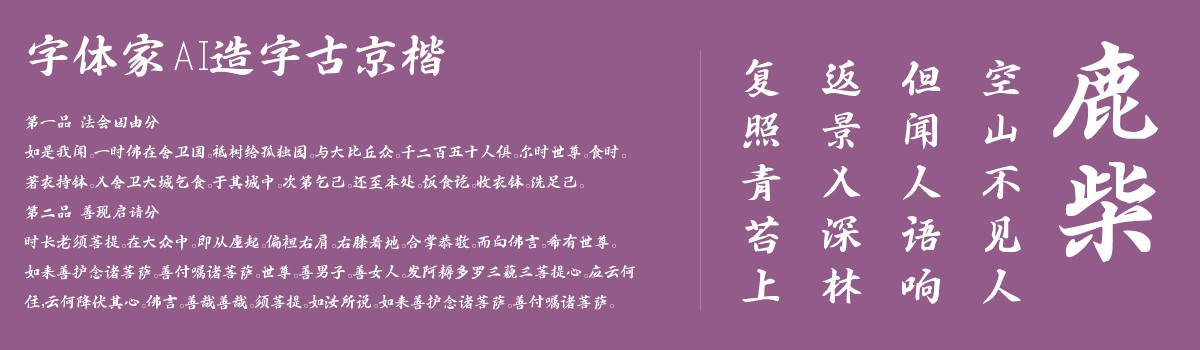
字体家AI造字古京楷
字体家AI造字古京楷是一款由字体家AI神笔造字生成的艺术字体,此字体笔画横平竖直,起收笔处见清晰顿挫,如刀削般利落却带着墨韵的温润。结构方正端庄,部件比例匀停,重心沉稳如磐石落定。线条粗细变化自然,横画舒展如平畴千里,竖画挺拔似孤松立崖,撇捺如鸟翼轻展,收锋处带着含蓄的力道。整体兼具楷书的规整与古韵的雅致,刚柔相济,耐看且有书卷气,仿佛能触到传统笔墨的沉静质感。适合用于一些广告标题、平面文案、海报标题、网页广告用字的编辑。